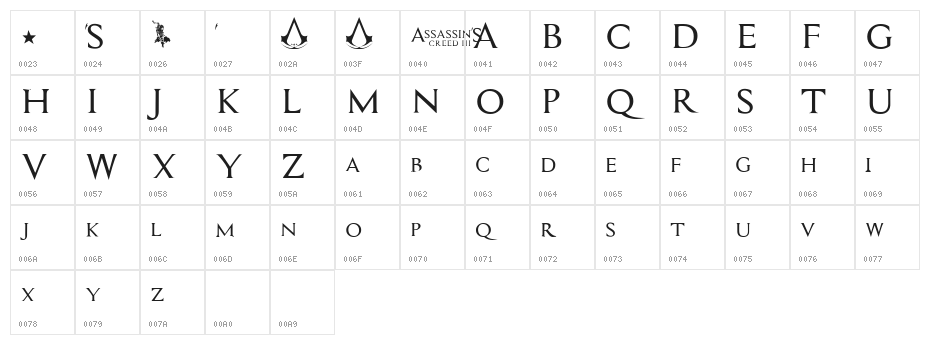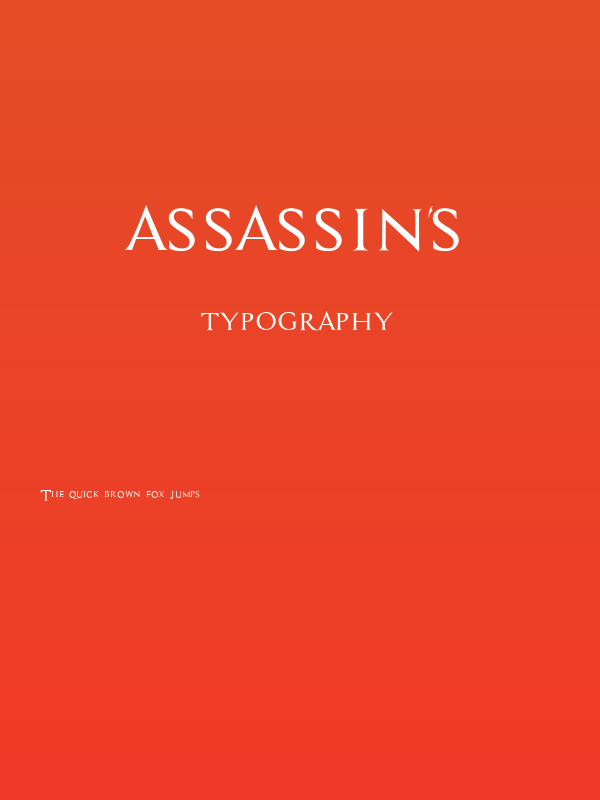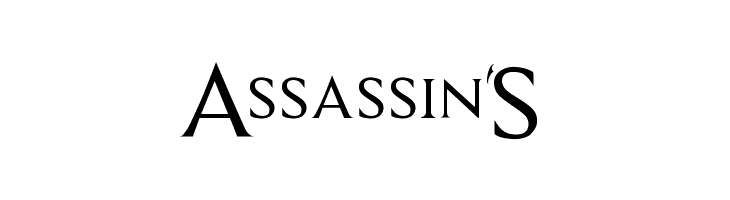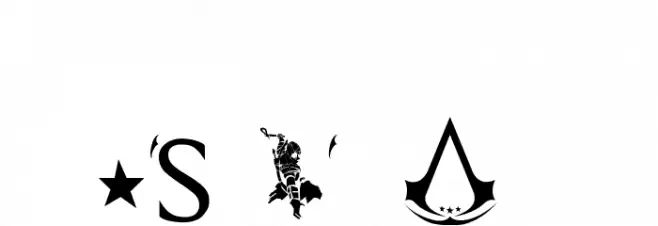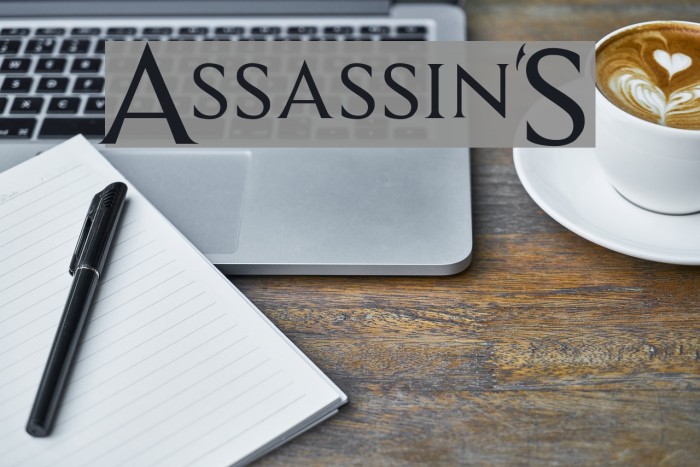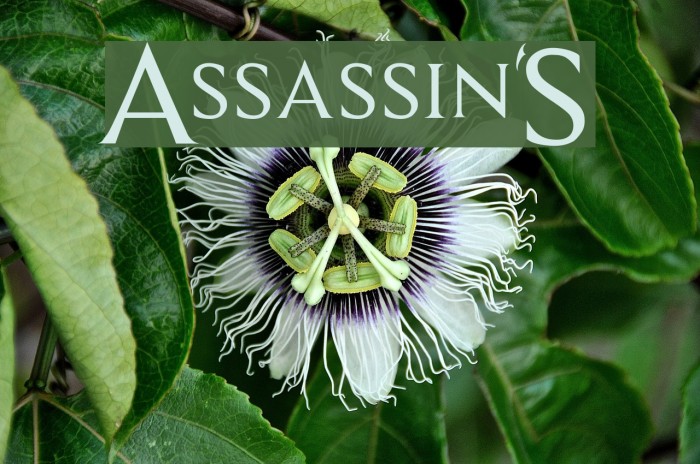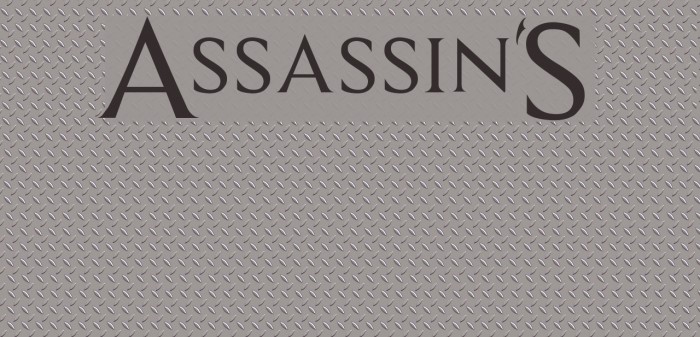
Assassin$ Font
✎ Serif
| 分类 | Serif |
| 整体风格 | Classic |
| 使用场景 | Headlines, Body text, Logos |
| 推荐项目 | Ideal for book covers, formal invitations, branding for luxury products, and editorial design. |